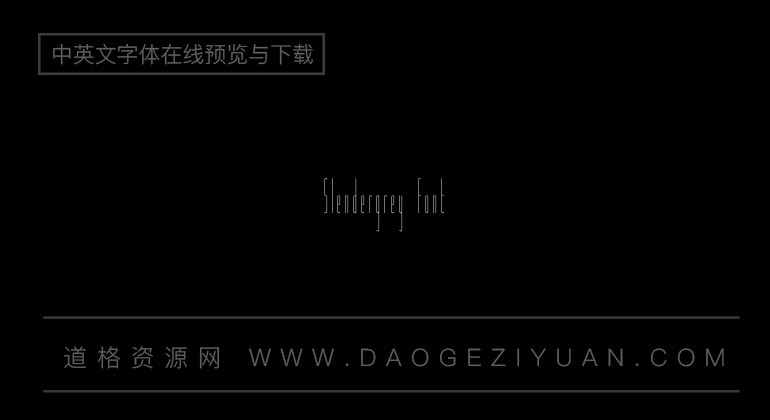
Slendergrey Font
Slendergrey Font 是一种现代化的无衬线字体,由设计师 Jonathan S. Harris 创作。这种字体具有简洁、流畅、时尚的特点,适用于各种设计项目,如品牌标识、海报、广告、包装等。Slendergrey Font 字体包括四种字重,包括 Light、Regular、Medium 和 Bold,可以根据设计需求选择不同的字重。此外,该字体还支持多国语言,包括英语、法语、西班牙语、德语等。如果你需要一种干净、现代的无衬线字体,Slendergrey Font 可能是一个不错的选择。
Slendergrey Font是一款非常不错的手写艺术字体,具有很好的视觉感,适合于文化类的宣传设计、商业类品牌的广告和产品包装设计以及个性化文字排版等较多场景。